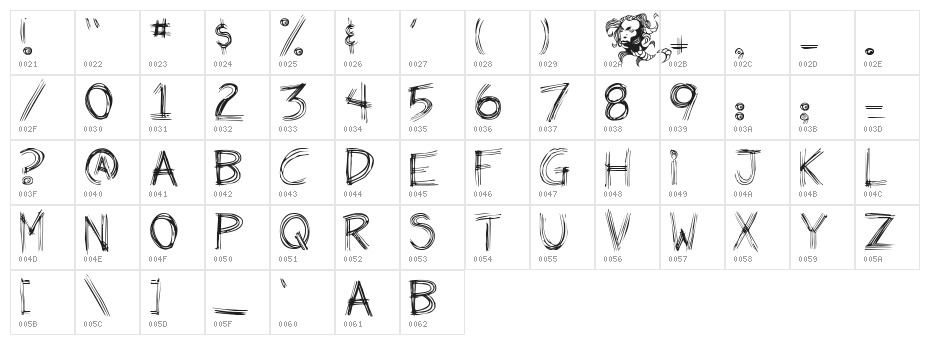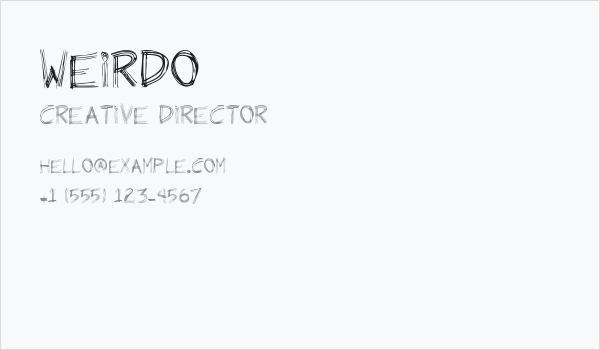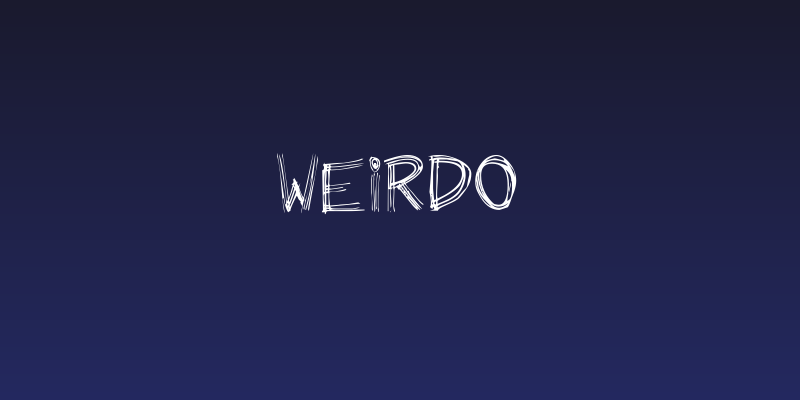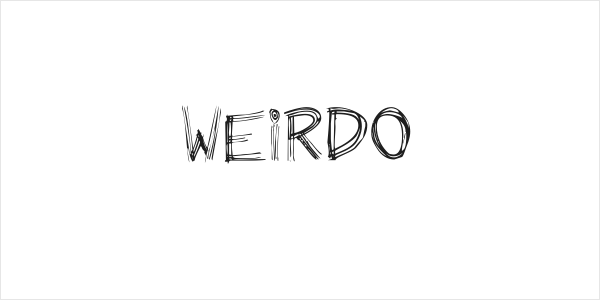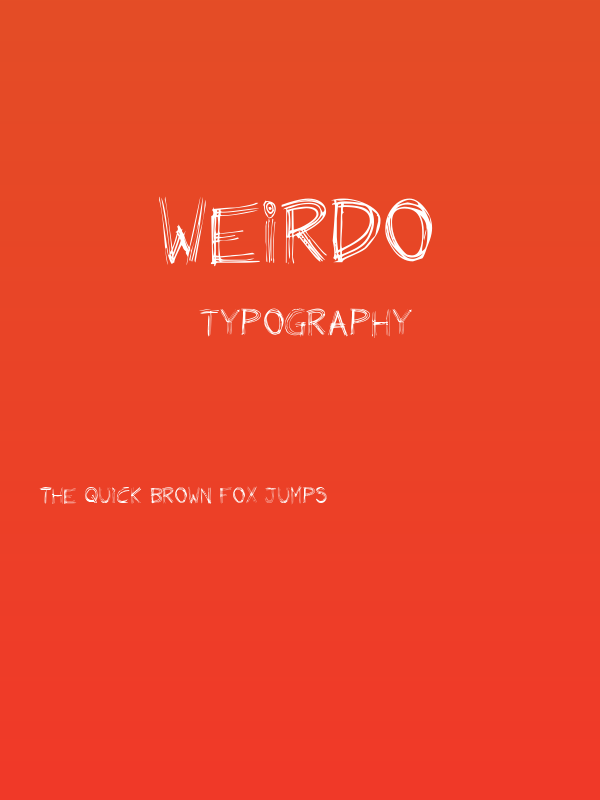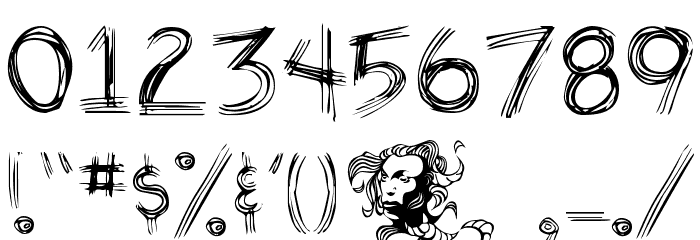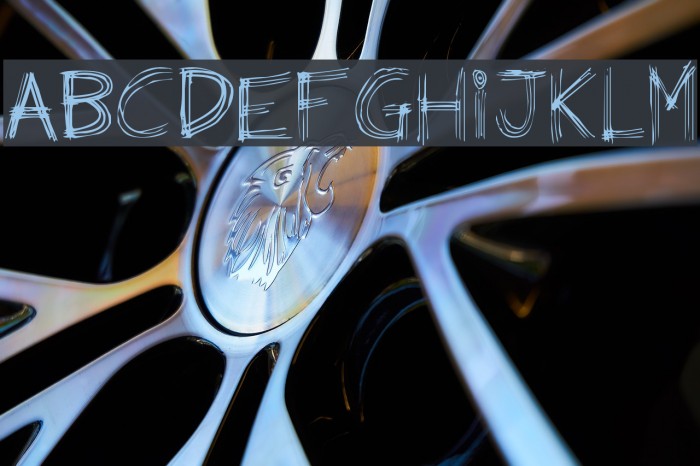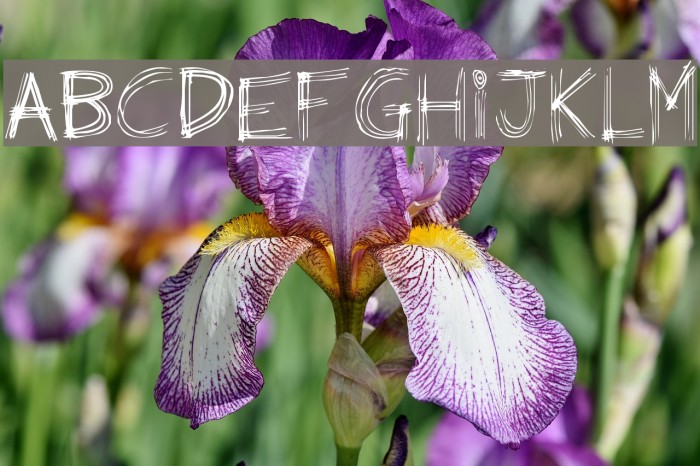
Weirdo Font
✎ Quirky
| Estilo general | Whimsical |
| Proyectos propuestos | Ideal for children's books, playful branding, artistic posters, and creative invitations. |